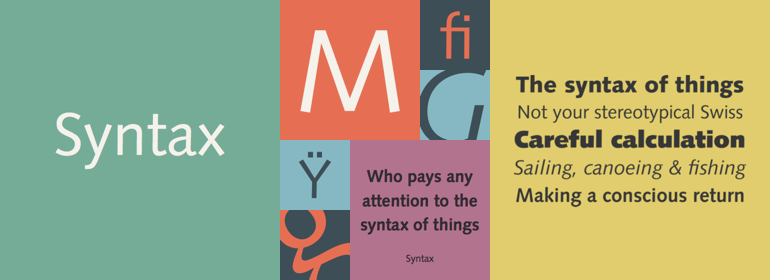
Syntax®
Syntax®,这款字体结构工整、笔画清晰,兼顾美观与易读性,适用于标题、正文、海报、包装、LOGO 等多种场景。字形优雅稳定,风格百搭耐看,适配日常排版与创意设计,让文字呈现更舒适、更具质感。Syntax®一笔一画,皆是细节,以均衡的比例、流畅的线条打造舒适视觉体验,字形端正大气,风格简约现代。无论是商业设计、品牌宣传还是日常排版,都能轻松驾驭,让文字更有格调与力量。Syntax®字体下载。
Syntax™ was designed by Swiss typographer Hans Eduard Meier, and issued in 1968 by the D. Stempel AG type foundry as their last hot metal type family. Meier used an unusual rationale in the design of this sans serif typeface; it has the shapes of humanist letters or oldstyle types (such as Sabon), but with a modified monoline treatment. The original drawings were done in 1954; first by writing the letters with a brush, then redrawing their essential linear forms, and finally adding balanced amounts of weight to the skeletons to produce optically monoline letterforms. Meier wanted to subtly express the rhythmical dynamism of written letters and at the same time produce a legible sans serif typeface. This theme was supported by using a very slight slope in the roman, tall ascenders, terminals at right angles to stroke direction, caps with classical proportions, and the humanist style a and g. The original foundry metal type was digitized in 1989 to make this family of four romans and one italic. Meier completely reworked Syntax in 2000, completing an expanded and improved font family that is available exclusively from Linotype GmbH as Linotype Syntax."